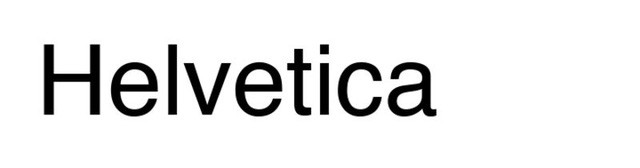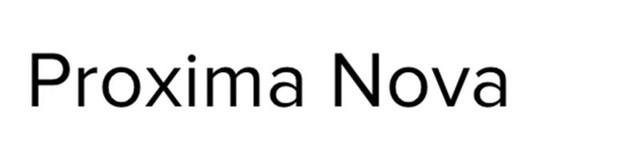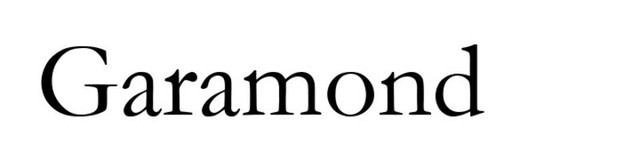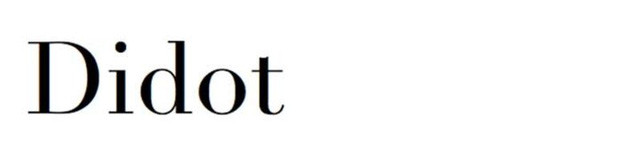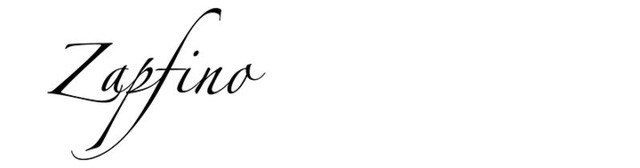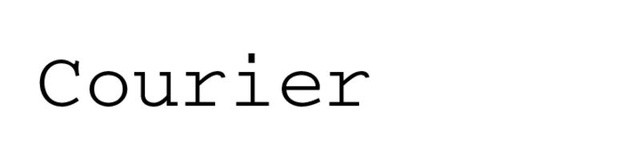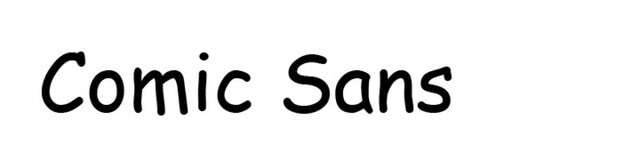
Sử dụng font chữ Times New Roman trong CV chẳng khác nào “mặc quần thể thao” đi xin việc
Khi viết CV xin việc bạn thường lựa chọn phông chữ nào để viết? Nếu bạn lựa chọn font chữ Time New Roman cho CV thì chẳng khác nào "mặc quần thể thao" đi phỏng vấn xin việc. Khi viết văn bản hầu hết chúng ta đều lựa chọn font chữ quen thuộc này, nó không hoàn toàn sai, nhưng không phải là font chữ phù hợp nhất để bạn có thể cho vào CV xin việc.
Một bản sơ yếu lý lịch (hay còn gọi CV) là một phần không thể thiếu cho các cuộc phỏng vấn xin việc, bản sơ yếu lý lịch này không chỉ phản ánh trình độ học tập và kinh nghiệm làm việc của bạn mà nó giúp nhà tuyển dụng nhìn nhận được phong cách riêng, sức sáng tạo của bạn khi viết CV. Tuy nhiên, trong chúng ta không phải ai cũng thành công trong việc thể hiện bản thân qua CV. Rất nhiều người đã mắc những sai lầm ngớ ngẩn như cách chọn font chữ không phù hợp đã làm bạn mất điểm trước mặt nhà tuyển dụng mà không hề hay biết.
Lâu nay chúng ta thường quan niệm rằng, những công việc liên quan tới thiết kế hoặc đồ họa thì mới cần quan tâm đến việc lựa chọn font chữ trong CV xin việc. Tuy nhiên quan niệm này hoàn toàn sai lầm!
Vậy trong những font chữ thường dùng hiện nay, font nào nên được chọn để viết CV. Hãy tham khảo những đánh giá từ các chuyên gia dưới đây nhé!
1. Font chữ Helvetica
Font chữ Helvetica
Nếu muốn lựa chọn font chữ rõ ràng, đơn giản, không quá cầu kỳ và không thiên theo một xu hướng nào thì font chữ Helvetica sẽ là một sự lựa chọn hoàn hảo cho bạn khi viết CV. Khi dùng font chữ này trông bạn sẽ chững chạc, đứng đắn hơn. Hơn nữa, nếu CV của bạn bao gồm rất nhiều kinh nghiệm, hoạt động khác nhau, sử dụng font chữ đơn giản như thế này sẽ giúp bạn tiết kiệm được nhiều khoảng trống để "nhồi nhét" hết những thành tích ấn tượng của mình đó. Và đây cũng là font chữ khá an toàn và có lẽ đó là lý do nó được sử dụng nhiều trong kinh doanh.
Bên cạnh đó, bạn cũng có một vài lựa chọn khác tương tự như Helvetica, chẳng hạn font chữ Sans-serif – không có "chân" nhỏ gạch bên dưới mỗi ký tự như font Times New Roman.
2. Proxima Nova sẽ là một sự lựa chọn tuyệt vời cho CV
Proxima Nova sẽ là một sự lựa chọn tuyệt vời cho CV
Nếu bạn muốn có một font chữ có nhiều ưu điểm như Helvetica, nhưng có ít "cạnh" hơn, thì font chữ Proxima Nova cũng sẽ là một sự lựa chọn tuyệt vời cho CV của bạn. Font chữ này mang lại cảm giác nhẹ nhàng hơn. Trong khi Helvetica có vẻ cứng rắn và nghiêm túc thì Proxima Nova lại mềm mại và tròn trịa hơn. Hầu hết các nhà tuyển dụng và khách hàng đều thích font chữ này. Tuy nhiên đây lại không phải là font chữ miễn phí, bởi lẽ cái đẹp thường phải trả giá đắt và nếu bạn muốn sở hữu font chữ này thì bạn cần bỏ ra 29,99$ để mua một loại của font chữ này trên myfonts.com và 734$ cho toàn bộ 144 loại khác nhau.
3. Nếu muốn định hướng người đọc thì hãy chọn font Garamond
Nếu muốn định hướng người đọc thì hãy chọn font Garamond
Nếu Helvetica vừa rõ vừa nhỏ, giúp bạn tiết kiệm không gian, còn Proxima Nova thì lại có cái giá quá đắt thì bạn vẫn còn một sự lựa chọn nữa đó là font Garamond. Nếu như bạn đã có rất nhiều kinh nghiệm rồi, hãy dùng font chữ này để thể hiện hết những kinh nghiệm đó lên một diện tích giới hạn cho phép. Theo các nhà thiết kế chuyên nghiệp, font chữ này giúp định hướng người đọc rất tốt. Bạn chỉ cần có vậy thôi, phải không?
4. Font chữ phổ thông Times New Roman
Font chữ phổ thông Times New Roman
Cho tới bây giờ, vẫn còn rất nhiều tranh cãi về font chữ phổ thông Times New Roman. Vì có một bộ phận không nhỏ các nhà thiết kế vẫn công nhận Times New Roman là chuẩn mực của tất cả các tài liệu được soạn thảo trên máy vi tính. Một số người cho rằng font chữ Times New Roman nhìn rườm rà, rối mắt, cần phải thay thế. Tuy nhiên font chữ này quá phổ biến và dùng theo hệ thống suốt cả chiều dài lịch sử. Tuy nhiên, nó được sử dụng vừa đúng vừa sai trong nhiều trường hợp. Nếu dựa trên tiêu chí thiết kế thế hệ mới bây giờ (rõ, đơn giản, đẹp mắt) thì có lẽ font Times New Roman không sánh bằng những font chữ kể trên.
5. Didot một font chữ cao cấp
Didot một font chữ cao cấp
Nếu bạn muốn có một font chữ cao cấp thì Didot cũng không phải là một gợi ý tồi. Font chữ này đem lại cho CV của bạn một sự sang trọng và nữ tính. Đây được cho là một sự lựa chọn hoàn hảo cho những người có công việc liên quan đến thiết kế thời trang. Tuy nhiên font chữ này lại không được sử dụng quá phổ biến khi soạn thảo văn bản.
6. Zapfino sẽ rất phù hợp cho những bức thiệp cưới
Zapfino sẽ  rất phù hợp cho những bức thiệp cưới
Còn đối với font chữ Zapfino thì các bạn nên tránh dùng, bởi nó quá rườm rà và cầu kỳ, nó chỉ phù hợp khi bạn làm thiệp cưới mà thôi. Đây là font chữ mang màu sắc gia đình chứ không nên sử dụng trong công việc vì nó quá khó đọc.
7. Courier cũng là font chữ bạn nên tuyệt đối tránh trong CV
Courier cũng là font chữ bạn nên tuyệt đối tránh trong CV
Courier cũng là font chữ bạn nên tuyệt đối tránh trong CV của mình. Bởi lẽ font chữ này hơi giống mô phỏng nét của máy đánh chữ hồi xưa. Đôi khi chính cái vẻ cổ xưa đó sẽ gây ấn tượng không tốt đối với nhà tuyển dụng trong thời đại mới này đó. Nét chữ nết người mà, biết đâu họ sẽ nghĩ bạn là một con người luôn sống trong cái cũ, không mở lòng cho cái mới, và chậm chạp bắt nhịp với xu thế hiện đại thì sao?
8. Comic Sans lại là font chữ vô cùng tồi tệ cho CV xin việc
Comic Sans lại là font chữ vô cùng tồi tệ cho CV xin việc
Comic Sans lại là font chữ vô cùng tồi tệ cho CV xin việc của bạn. Font này chỉ dành cho các bạn "teen teen". Nếu bạn sử dụng font chữ này để làm CV thì chắc chắn nó sẽ là một thảm họa đấy. Chưa kể, font Comic Sans rất chiếm diện tích vì vậy bạn nên tuyệt đối tránh chọn font chữ cho CV.
9. Hãy chèn thêm một số biểu tượng cảm xúc cuối CV xin việc
Hãy chèn thêm một số biểu tượng cảm xúc cuối CV xin việc
Bạn từng băn khoăn có nên chèn các biểu tượng cảm xúc vào CV xin việc hay không? Lời khuyên của các chuyên gia là có, nhưng hãy đặt chúng ở cuối cùng hoặc bên lề. "Đó có thể là một ý tưởng tuyệt vời giúp bạn gây ấn tượng với nhà tuyển dụng thì sao"?